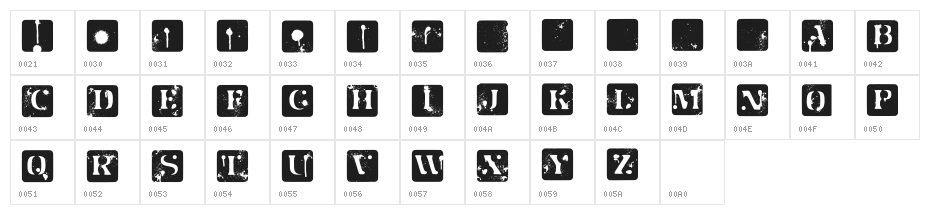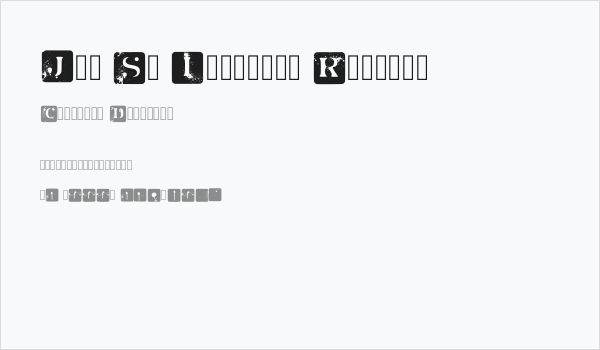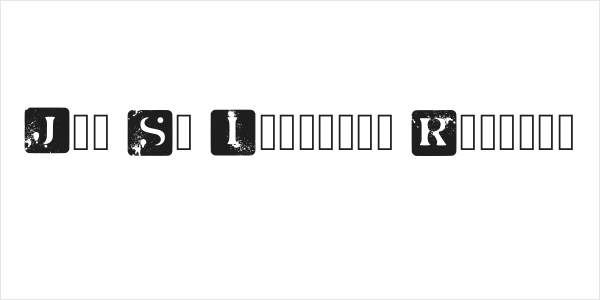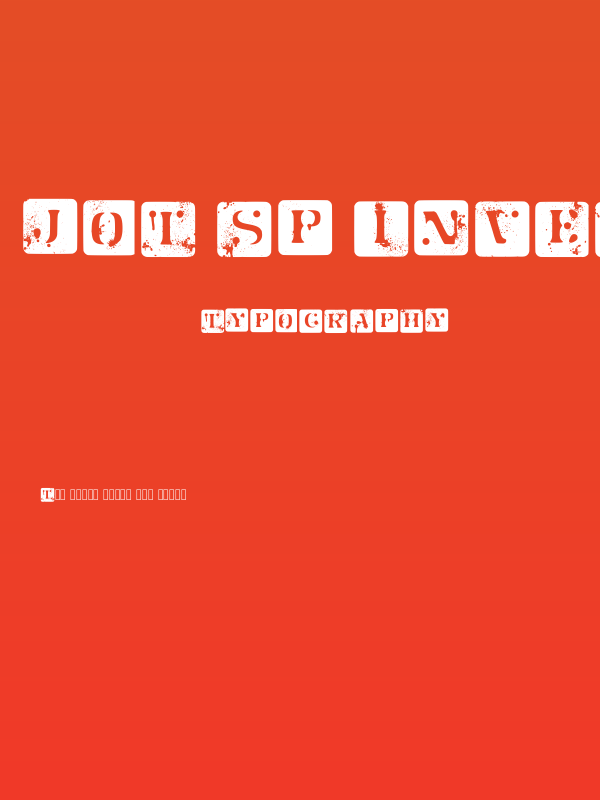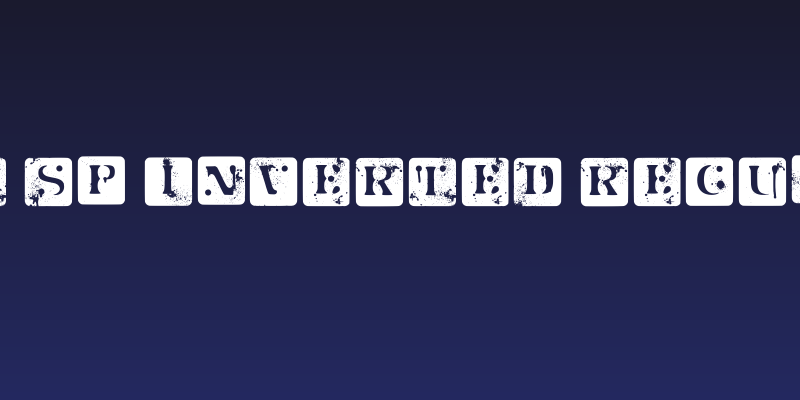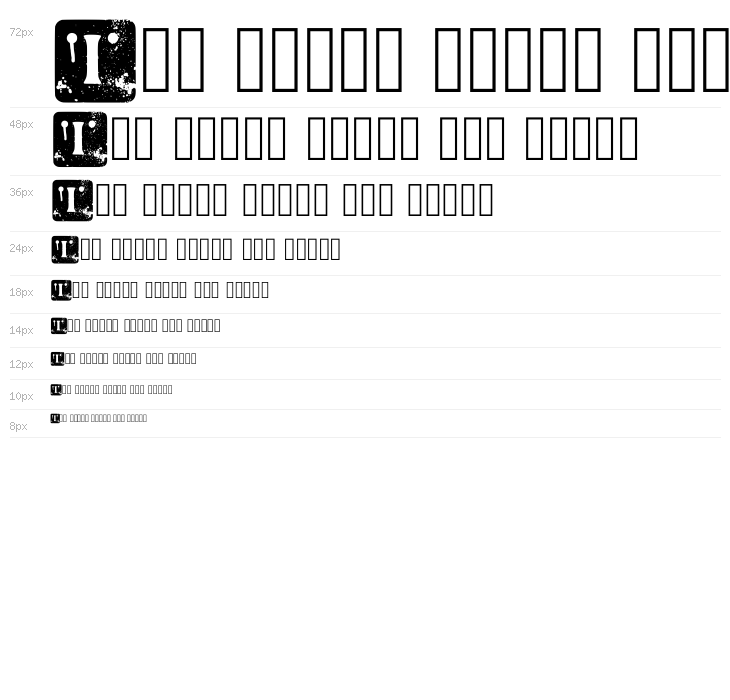
Jot Sp Inverted Regular Font
| Progetti proposti | Ideal for posters, album covers, branding materials, and any design requiring a strong, edgy aesthetic. |